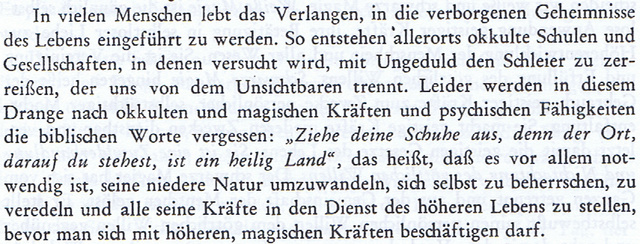
Buchschrift aus den 50er Jahren
diese Schrift findet sich auf einer esoterischen Abhandlung aus den 50er Jahren:
Ich soll sie identisch nachsetzen. Wer kann die Schriftart erkennen und benennen?
Wobei das exakte Nachsetzen schwierig wird, selbst mit der Stempel Garamond, denn die erhältlichen digitalen Versionen unterscheiden sich doch erheblich von der alten Linotype-Zeilenguß-Version. Auch das typische Linotype-Druckbild wird man mit den neuen Versionen nicht exakt hinbekommen.
Am ehesten könnte noch die Garamond SB passen:
Die Stempel-Garamond auf der Linotype setzen lassen und im Buchdruck drucken ... und schon siehts fast ganz genauso aus. Wenn Du noch einen Lino-Setzer kennst oder findest - die Stempel-Garamond-Matrizen waren weitverbreitet und finden sich in den allermeisten der wenigen noch arbeitenden Linotypebleisetzwerkstätten ...